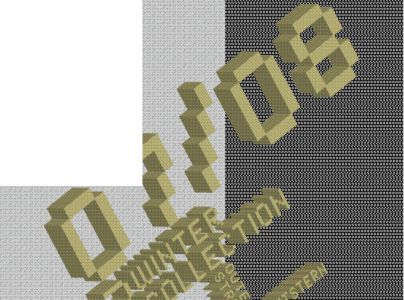
Schriftart von dem Hintergrund von zimtstern.com
Hab da mal ne Frage: Kennt jemand den Namen der Schriftart die im Background von zimtstern.com vorkommt?
Oder wenigstens eine, welche sich ähnelnd...könnte ich mir dann viel Arbeit im Photoshop ersparen :)...
Du meinst das braune?
eine Pixelschrift (bleibt die Frage welche), in Illustrator in 3D gedreht und extrudiert. Photoshop zu verwenden wäre da mühsam.
ja, die braune...bin nur im besitz vom photoshop cs2...aber es gibt ja zum glück eine testversion von illustrator...
nunja, aber gut dass du mich drauf aufmerksam gemacht hast...diese methode ( http://www.adobe.com/de/designcenter/il ... dline.html ) ist tatsächlich um einiges schneller als die im photoshop...
Dafür würde auch das Kostenlose Inkscape nötigenfalls voll ausreichen.
Guck mal bei dafont nach der "sf intermosaic", das ist eine kostenlose Pixelschrift. In der Kategorie "Techno" und dann "Squares" gibts auch Zeug in der Richtung, qualitativ halt dafont-Schrabbel aber vielleicht taugts dir ja was!
...und dann wie Sebastian gesagt hat im Illustrator extrudieren.